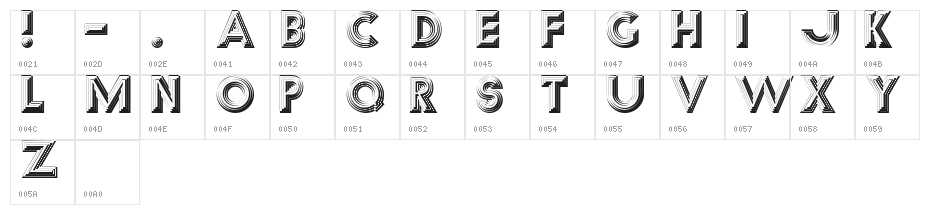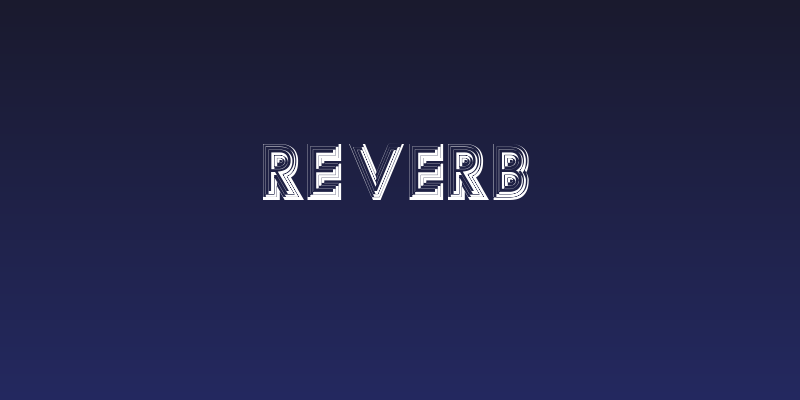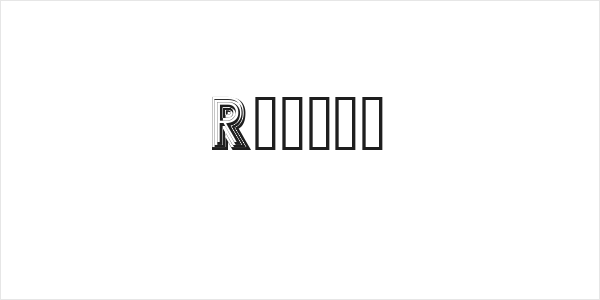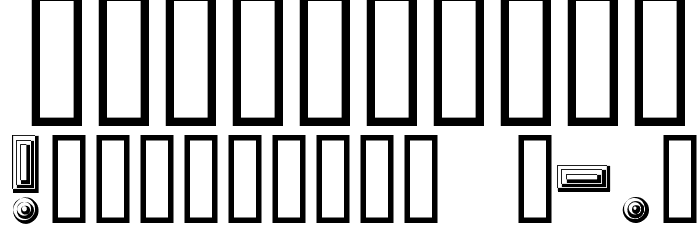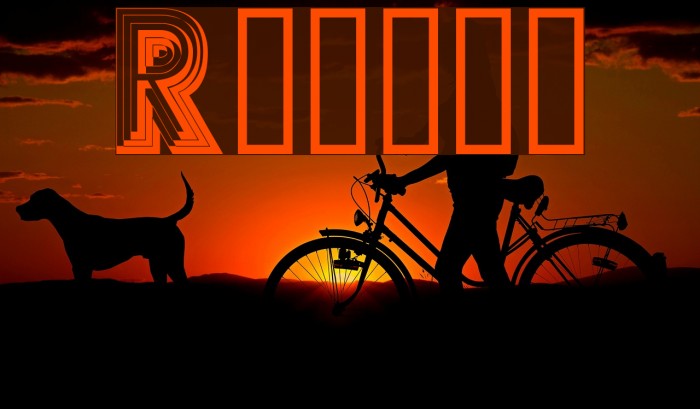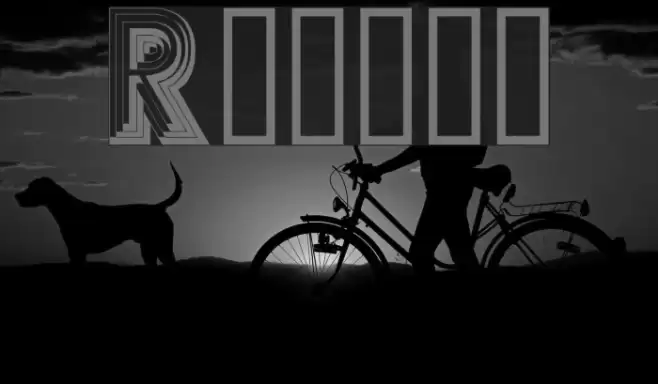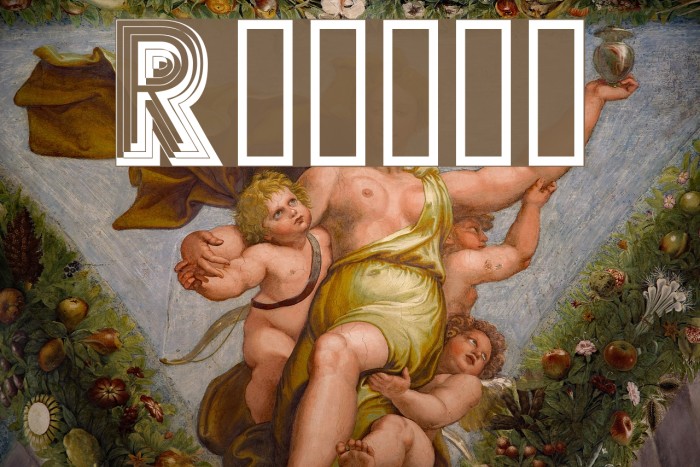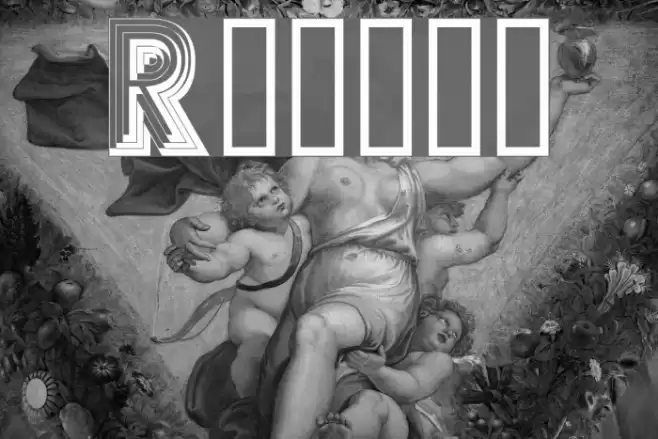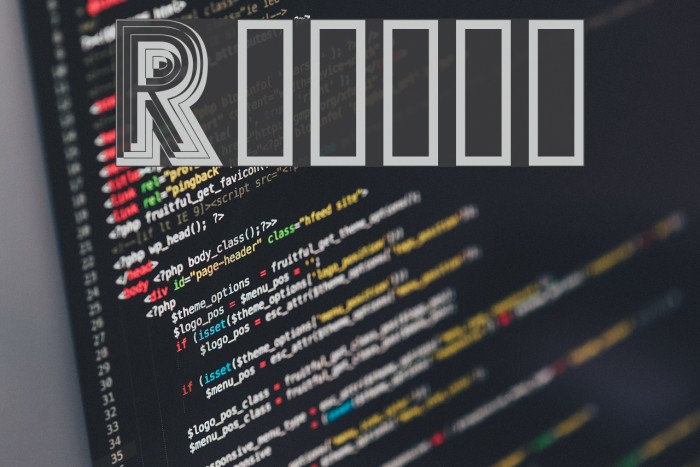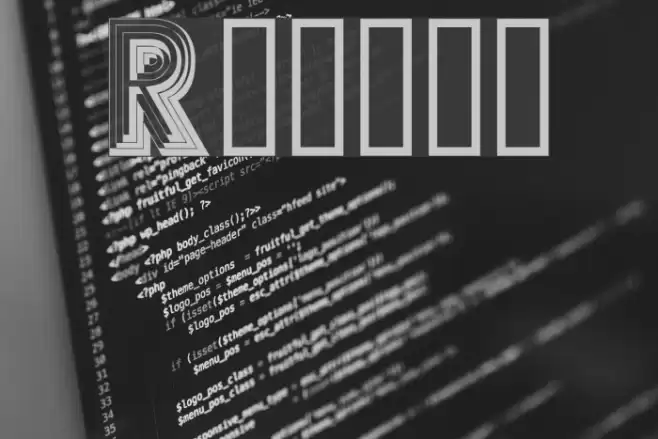
Reverb Font
✎ Capitals
| Nume | Reverb |
| Categorii | Capitals |
| Proiecte propuse | Ideal for retro-themed posters, vintage advertisements, album covers, and branding that requires a standout, nostalgic look. |